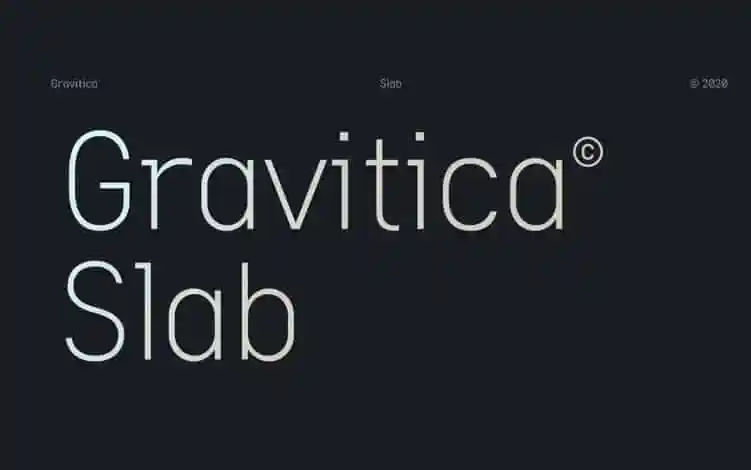
Gravitica Slab Font Demo
A fonte ‘Gravitica Slab’ é uma seleção fascinante de serifada com traços refinados e elegância suíça. Escolhida para atender à demanda crescente por tipos modernos, esta fonte foi meticulosamente cunhada para oferecer um toque sofisticado no entrelace das letras. Sujeita a opções de design extremamente detalhadas, cada peso da fonte contém suporte linguístico extenso que inclui conjuntos de alfabeto ocidental e europeu central, garantindo facilidade na criação de textos em diferentes idiomas. Com foco na interação e personalização das letras, a ‘Gravitica Slab’ vem acompanhada de 6 pesos, 12 tipos direitos e suas respectivas itálicas, permitindo que você use sua plenitude para expressar ideias e conceitos com estilo. Desenvolvida para oferecer benefícios únicos da linguagem opentype, cada peso inclui suporte linguístico extenso, proporções de fração, números tabulados, símbolos, ligas, ícones e padrões, tornando-a uma fonte versátil que se adapta perfeitamente a qualquer projeto. Com ‘Gravitica Slab’, você pode explorar formas criativas e expressar sua personalidade de maneira única em qualquer aplicação visual.